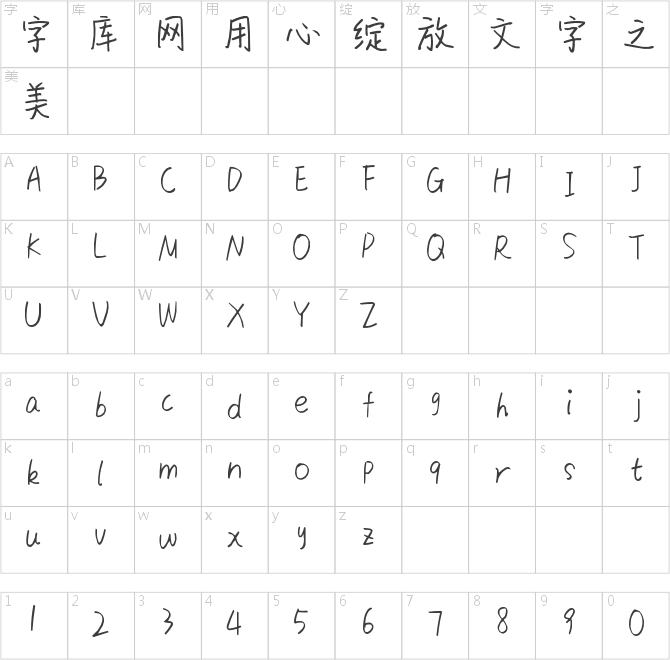
字体名称: 我想我是忧伤的
我想我是忧伤的
该字结字俊秀隽永,行笔自然洒脱,收笔带点,如翩翩公子,意气风发。适用于文艺类的书刊、品牌广告和产品包装设计,以及社交网络的个性化用字。
我想我是忧伤的字体FZSJ-WOXWSYSD字库是一款让人赏心悦目、百看不厌的中文字体,适合各类广告和产品包装设计应用,字体大小3.75MB,格式为TTF字体,上传用户是saber,作者/版权方为方正手迹